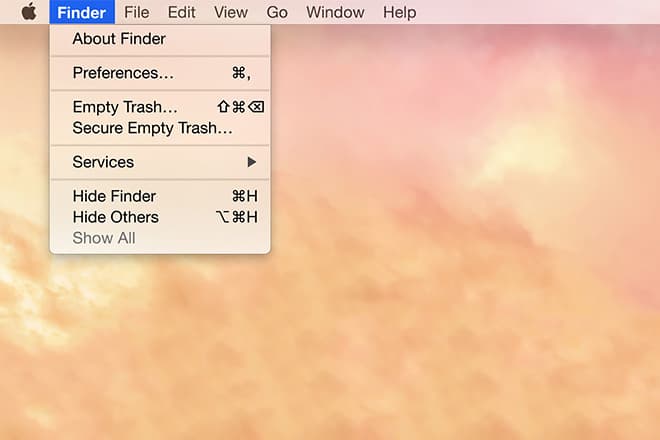
Apple 自 2001 年以来首次改变桌面操作系统默认字体
在 2014 年度的 WWDC 全球开发者大会上,Apple 正式公布了新一代桌面操作系统 OS X Yosemite。相较于上一代 Mavericks 系统,Yosemite 在界面的风格上有了颠覆性的变化。无论是重新设计的系统图标、顶部半透明且鲜亮的工具栏背景,亦或是通知中心,都更加趋向于 iOS 操作系统的扁平风格。为了适应这种风格,Apple 也是自 2001 年以来首次改变了系统的默认字体。原本的默认字体是 Lucida Grande,并且伴随著 OS 的用户度过了 13 年的时间,不过现在却改成了更加纤瘦的 Helvetica Neue 字体,从而在 Retina 视网膜显示屏中进一步提升用户的易读性。